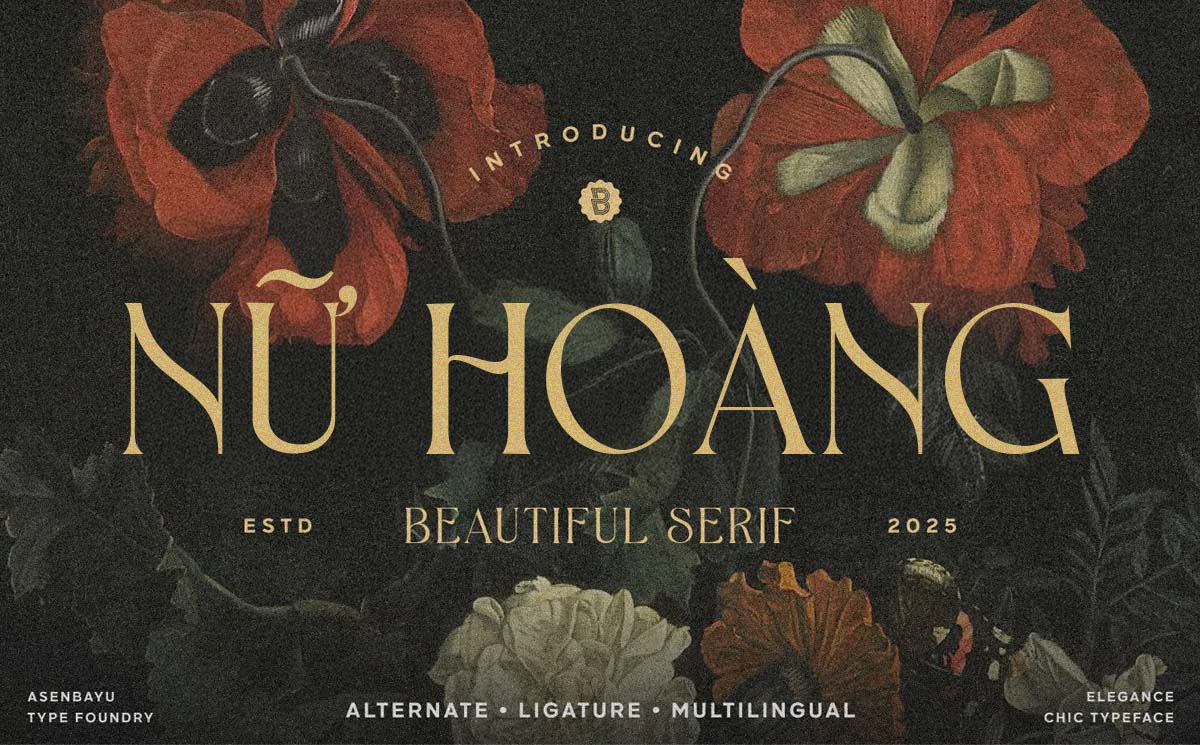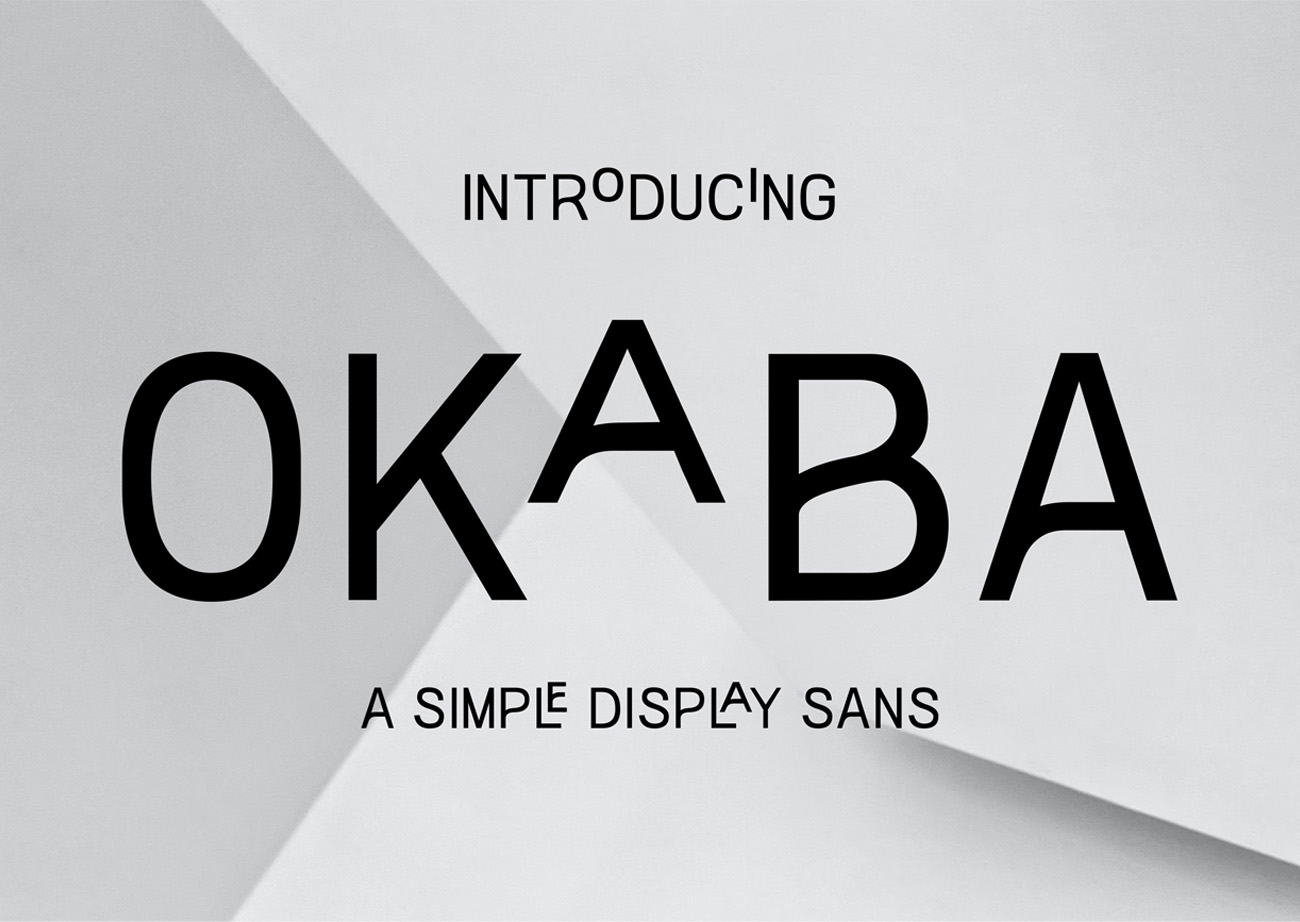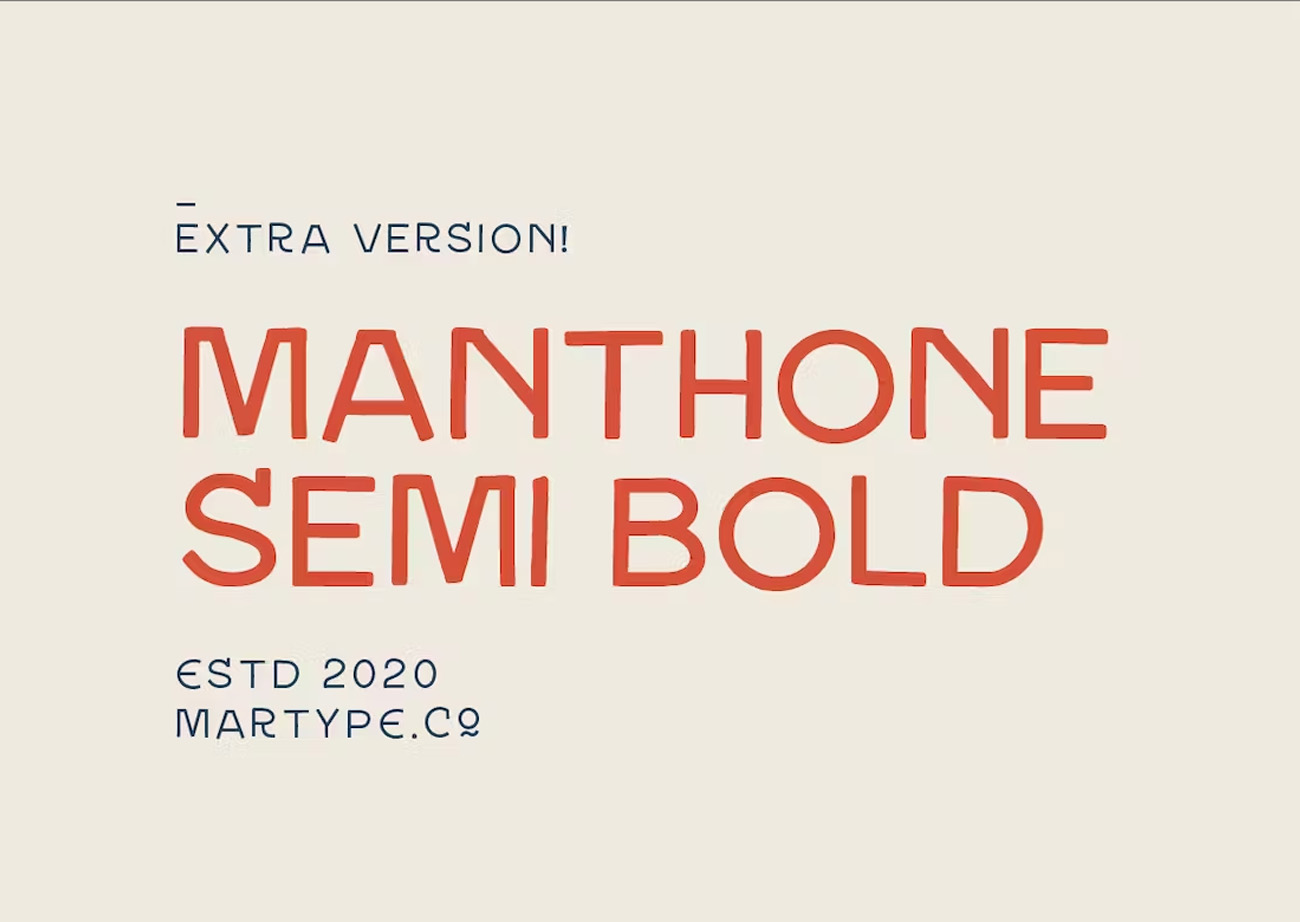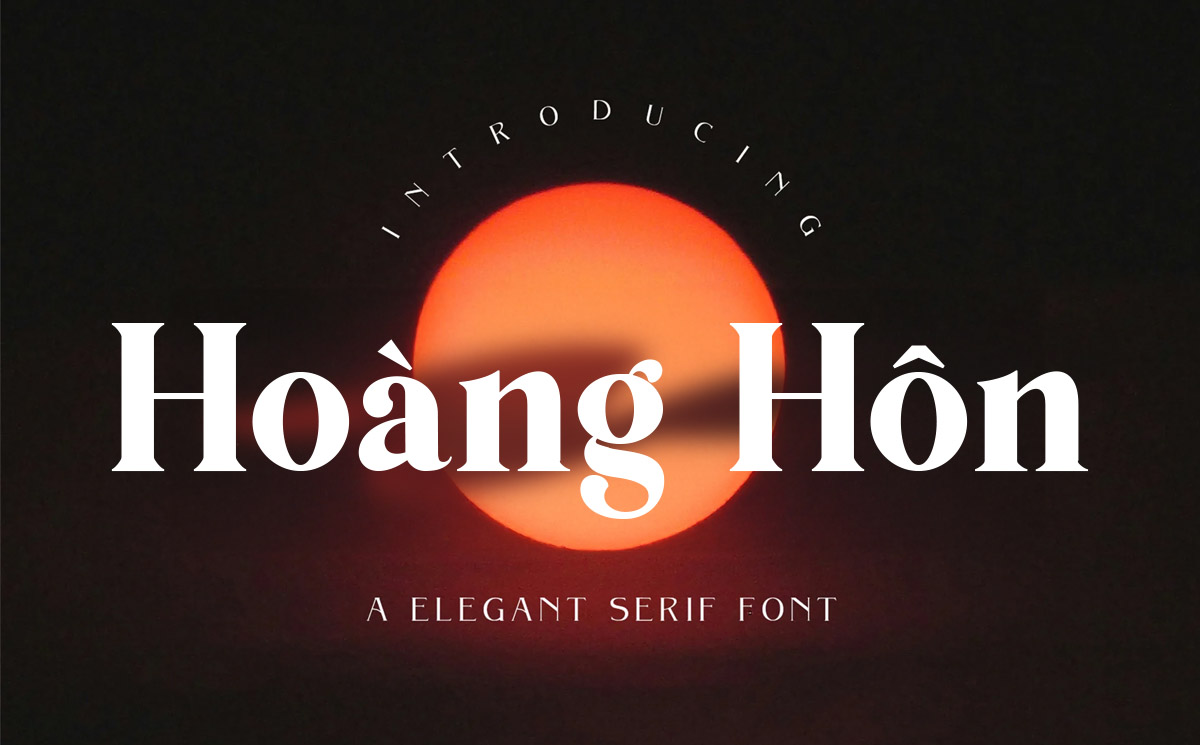
Font chữ chân phương – Tổng hợp font chữ đơn giản, rõ nét và dễ sử dụng
Font chữ chân phương là nhóm các phông chữ mang phong cách giản dị, chuẩn mực, gọn gàng và có độ dễ đọc (legibility) tuyệt đối, rất được ưa chuộng trong ngành xuất bản sách báo, văn bản hành chính và thiết kế bao bì sản phẩm. Với đặc trưng là cấu trúc chữ minh bạch, không phô trương hay cầu kỳ, phông chữ chân phương giúp người xem dễ dàng tiếp nhận toàn bộ thông tin chi tiết như bảng thành phần, hướng dẫn sử dụng hay câu chuyện thương hiệu trên vỏ hộp. Doozypack.vn cung cấp link tải trọn bộ phông chữ chân phương chuẩn kỹ thuật, hỗ trợ đầy đủ tiếng Việt giúp bạn hoàn thiện các bản thiết kế chuyên nghiệp, rõ ràng nhất.
Đặc điểm thẩm mỹ độc đáo của bộ font chữ chân phương
Phông chữ chân phương không chạy theo các xu hướng trang trí hoa mỹ; sức mạnh của nó nằm ở sự khiêm nhường, tính kỷ luật của tỷ lệ chữ và sự thoải mái tuyệt đối cho mắt người đọc.
Mẫu chữ chân phương rõ nét
Sự giản dị, chuẩn mực và minh bạch trong từng con chữ
Đặc trưng lớn nhất của Font chữ chân phương là các đường nét được thiết kế theo tỷ lệ tối ưu, không có các chi tiết thừa thãi hay uốn lượn rườm rà. Thân chữ thẳng thắn, rõ ràng, mang lại cảm giác tin cậy, an toàn và gần gũi. Khi đặt phông chữ này làm nội dung mô tả trên bao bì, sản phẩm của bạn sẽ ngay lập tức toát lên vẻ chuyên nghiệp, minh bạch và tôn trọng tuyệt đối đối với người tiêu dùng.
Độ dễ đọc (Legibility) tuyệt đối cho các khối văn bản dài
Các ký tự của Font chân phương sở hữu khoảng hở trong chữ (counter) rộng rãi cùng x-height cân đối. Đặc điểm kỹ thuật này giúp mắt người dễ dàng lướt qua các đoạn văn bản dài mà không hề bị mỏi mắt. Đây là lý do nhóm phông chữ này luôn là “xương sống” trong việc dàn trang nội dung phụ (body text) trên mặt sau của mọi loại hộp giấy, túi giấy.
Ưu điểm nổi bật của bản phông chữ chân phương Việt hóa
Khi ứng dụng các phông chữ tiêu chuẩn vào thị trường trong nước, sự chỉn chu về dấu câu là yếu tố quyết định đến tính chuyên nghiệp của ấn phẩm:
• Khắc phục triệt để lỗi dấu tiếng Việt: Phiên bản Việt hóa chuẩn đã được đội ngũ thiết kế trau chuốt thủ công từng dấu câu. Các dấu sắc, huyền, hỏi, ngã, nặng được đặt ở vị trí thoáng đãng so với thân chữ, không gây cảm giác chắp vá hay đè nét làm mất tính thẩm mỹ.
• Tương thích chuẩn bảng mã Unicode: Bản font cho phép bạn dễ dàng soạn thảo nội dung trên các bộ gõ tiếng Việt thông dụng như Unikey hay EVKey, hiển thị mượt mà trên mọi phần mềm đồ họa hiện đại.
• Bảo đảm tính đồng nhất thương hiệu: Việc sử dụng bản font chuẩn giúp bạn tự tin dàn trang nội dung tiếng Việt mà không lo hiện tượng lỗi ô vuông hay nhảy về font hệ thống khô khan.
Kiểu chữ truyền thống thanh lịch
Nhóm Font Chân Phương Đặc điểm thị giác Ứng dụng đề xuất tại Doozypack.vn
Serif Chân Phương (Garamond, Times) Có chân, cổ điển, trang trọng In bảng thành phần dược phẩm, sách, hộp trà truyền thống.
Sans-serif Chân Phương (Roboto, Inter) Không chân, hiện đại, sạch sẽ Hướng dẫn sử dụng thiết bị, nhãn dán thông số kỹ thuật.
• Hộp giấy đựng Dược phẩm & Thực phẩm chức năng: Thông tin liều lượng, thành phần in bằng font chân phương giúp người dùng dễ dàng tra cứu, tạo niềm tin tuyệt đối về tính minh bạch của sản phẩm.
• Bao bì Trà thảo mộc & Nông sản mộc mạc: Kết hợp phông chữ chân phương cùng chất liệu giấy Kraft nâu tạo nên phong cách mộc mạc, gần gũi và chân thành.
• Sách hướng dẫn sử dụng & Catalogue đi kèm hộp quà: Dùng cho các nội dung văn bản dài bên trong hộp sản phẩm, giúp người đọc tiếp nhận thông tin một cách êm ái và dễ chịu nhất.
Thiết kế chữ đơn giản dễ đọc
Lưu ý kỹ thuật khi in ấn với phông chữ chân phương
Việc sản xuất bao bì thực tế sử dụng các phông chữ tiêu chuẩn đòi hỏi sự am hiểu kỹ thuật chuyên sâu tại xưởng in Doozypack.vn:
• Kiểm soát kích thước chữ tối thiểu: Trên chất liệu giấy Ivory nhẵn mịn, phông chữ chân phương hiển thị rõ ràng ở 5.5pt. Tuy nhiên, trên giấy Kraft thô nhám, bạn nên để size chữ tối thiểu từ 7pt trở lên để thớ giấy không làm mờ các chi tiết dấu thanh.